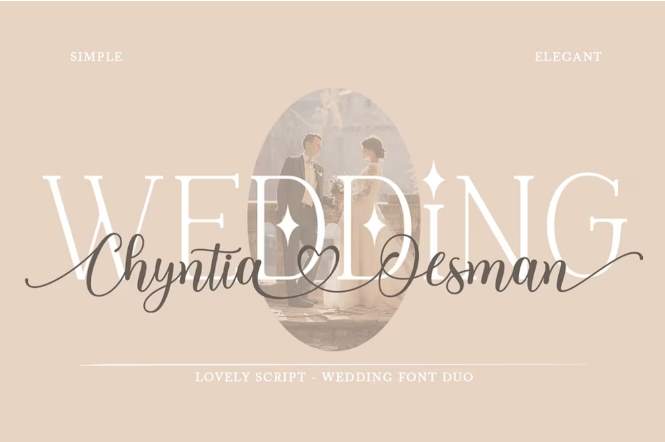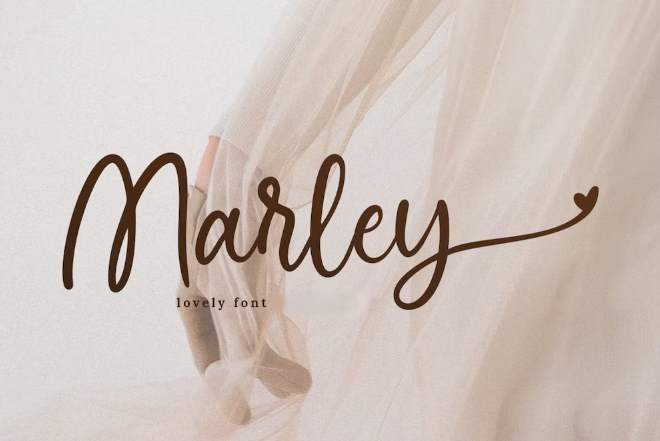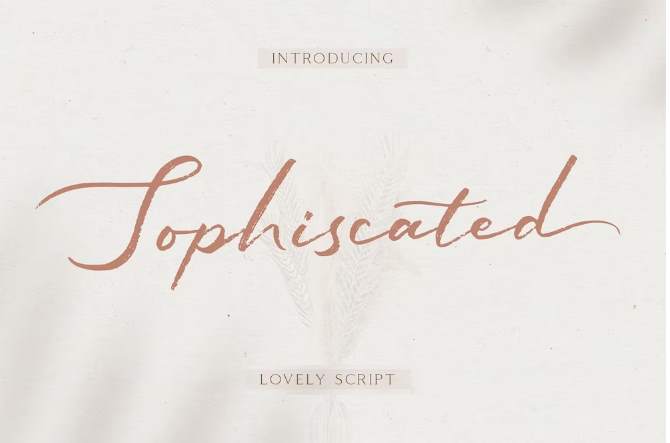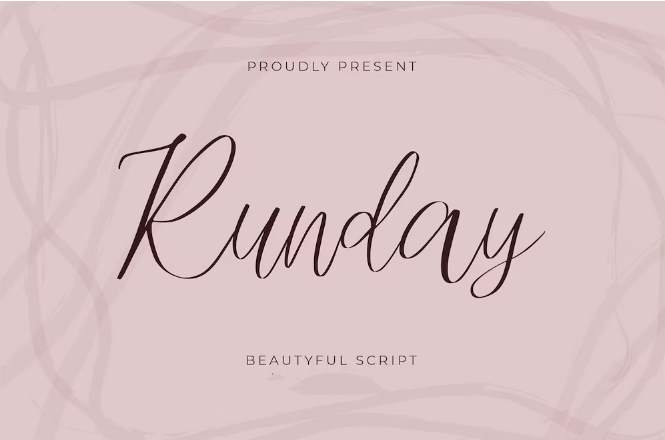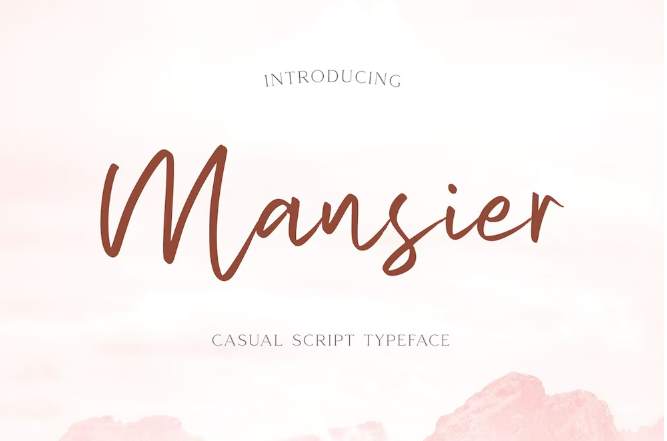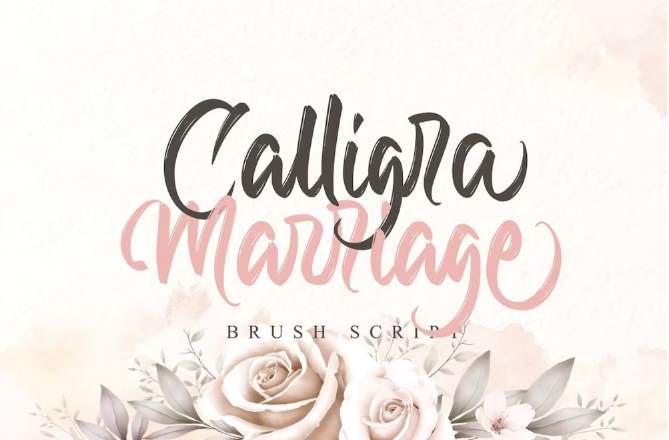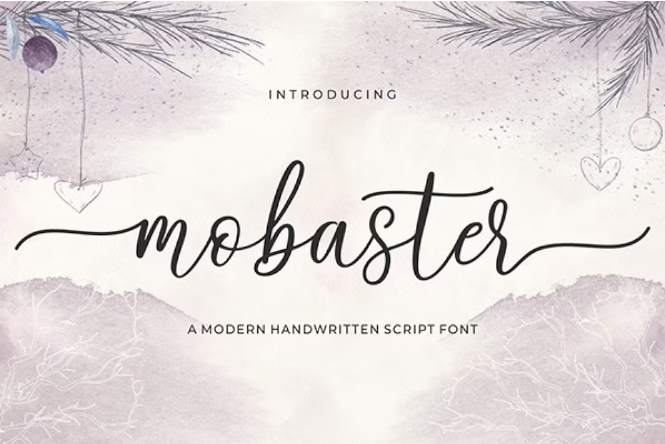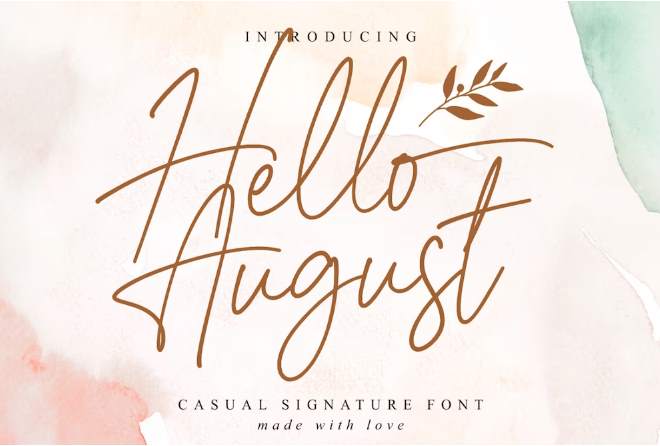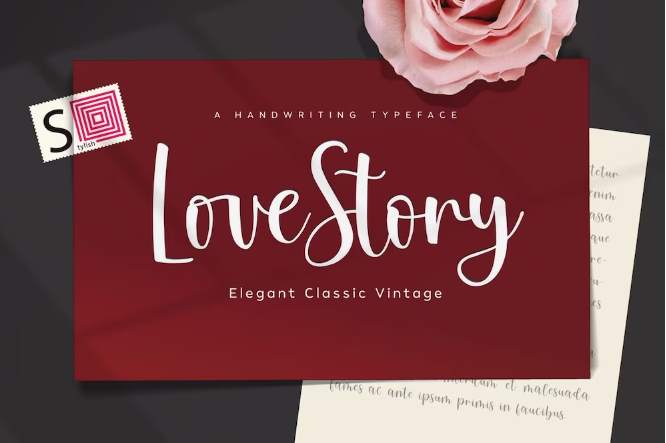
Chia Sẻ Bộ 10+ Font Chữ WEDDING Tuyệt Đẹp Miễn Phí
Bộ font chữ wedding miễn phí từ Sadesign.vn mang đến cho các designer những lựa chọn tuyệt vời để tạo ra các thiết kế thiệp cưới, invitation, hay các sản phẩm truyền thông cho đám cưới. Với những font chữ sang trọng và tinh tế, bộ sưu tập này giúp bạn dễ dàng tạo ra những sản phẩm ấn tượng, phù hợp với không khí lãng mạn của ngày trọng đại. Cùng khám phá cách tải bộ font chữ wedding miễn phí và ứng dụng chúng trong các dự án thiết kế của bạn.
1. Tại Sao Font Chữ Wedding Lại Quan Trọng Trong Thiết Kế?
Ngày nay, thiết kế đám cưới không chỉ đơn giản là việc lựa chọn màu sắc hay hình ảnh minh họa. Một yếu tố quan trọng không kém giúp tạo nên sự ấn tượng chính là font chữ. Đặc biệt, font chữ wedding (font chữ đám cưới) đóng vai trò chủ chốt trong việc thể hiện sự sang trọng và lãng mạn của các thiết kế liên quan đến đám cưới.
Font chữ không chỉ là phương tiện để truyền tải thông điệp mà còn là công cụ giúp thiết kế sản phẩm thêm phần sinh động và ấn tượng. Các font chữ đẹp, đặc biệt là các font dành riêng cho đám cưới, có thể giúp thiết kế của bạn trở nên bắt mắt và tinh tế hơn, tạo ấn tượng sâu sắc với khách mời.
Trong các thiết kế như thiệp cưới, thiệp mời, menu, hay bất kỳ sản phẩm đồ họa nào liên quan đến đám cưới, việc lựa chọn đúng font chữ wedding không chỉ giúp tạo ra vẻ đẹp thẩm mỹ mà còn phản ánh đúng không khí lễ hội, sang trọng và đầy lãng mạn của ngày cưới.
1. Sự Đa Dạng và Tinh Tế
Bộ font chữ wedding miễn phí từ Sadesign.vn mang đến sự đa dạng trong lựa chọn. Các font chữ này được thiết kế với các kiểu dáng khác nhau, từ những kiểu chữ mềm mại, thanh thoát đến những kiểu chữ mạnh mẽ, trang trọng. Tất cả đều mang lại một vẻ đẹp tinh tế và lãng mạn, giúp phù hợp với mọi phong cách thiết kế đám cưới.
Các thiết kế font chữ wedding trong thiết kế thiệp cưới tại sadesign.vn bên dưới:
3. Kết Luận